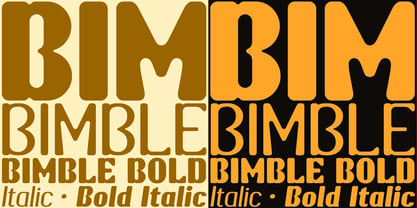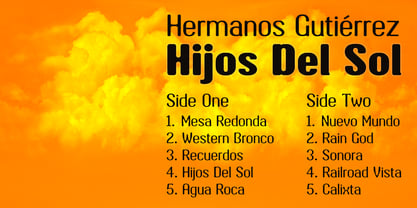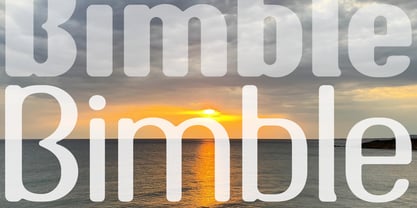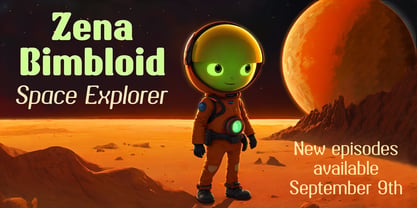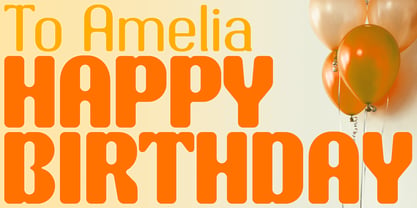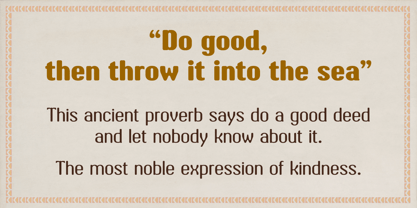
Bimble
La familia tipográfica Bimble fue diseñada por Keith Bates y publicada por K-Type. Bimble contiene 4 estilos y opciones de paquete familiar. Más información sobre esta familia
Bimble is a semi-condensed, sans-serif family of friendly, rounded characters.